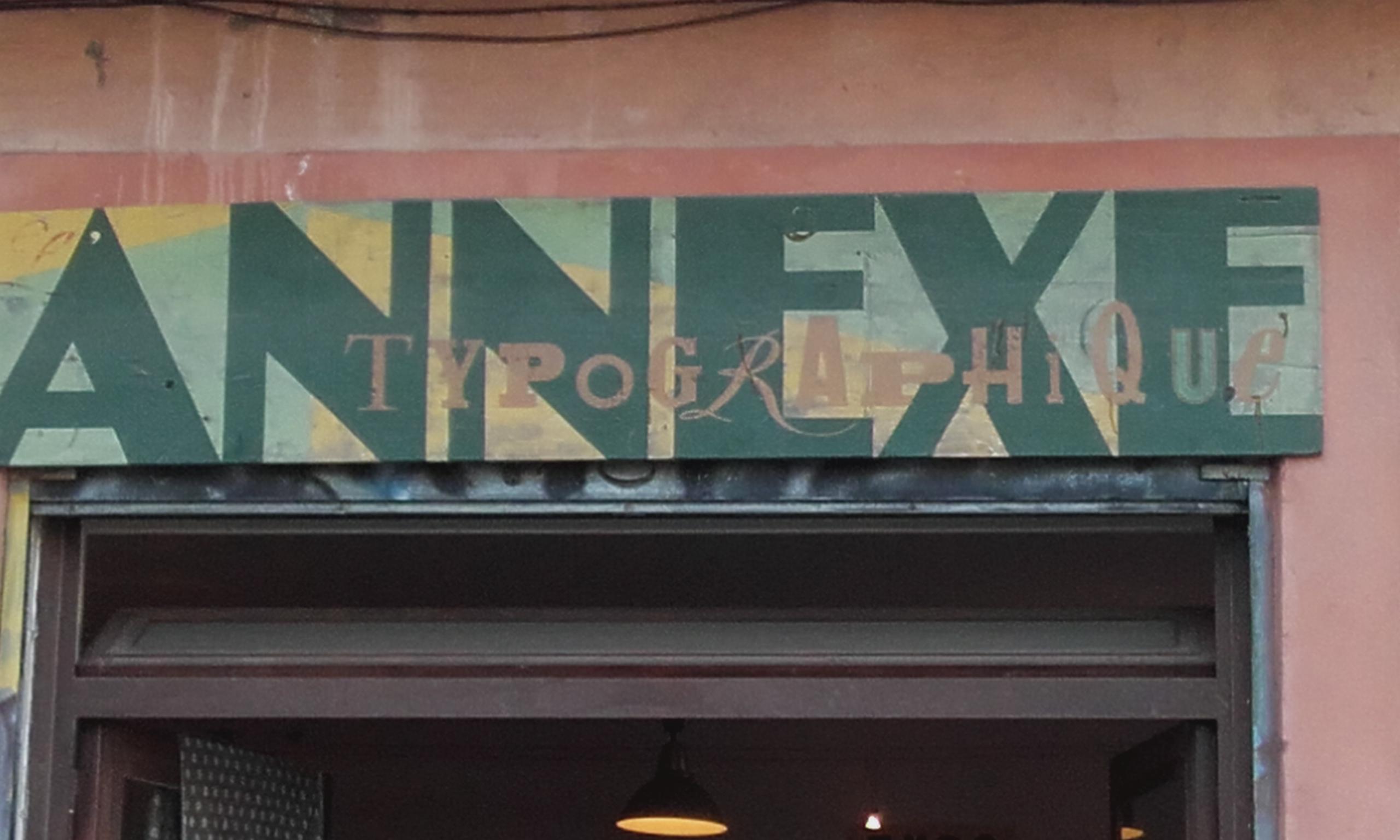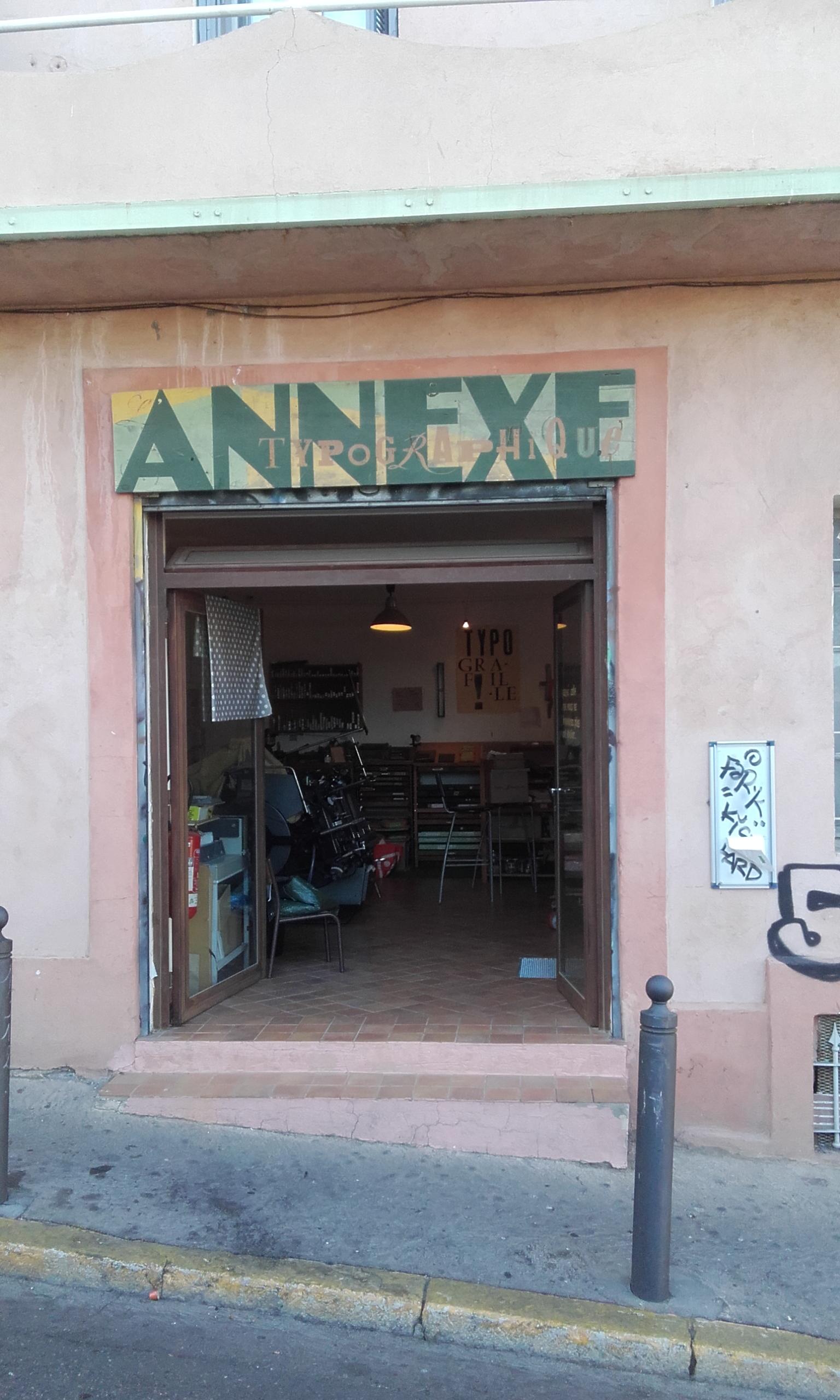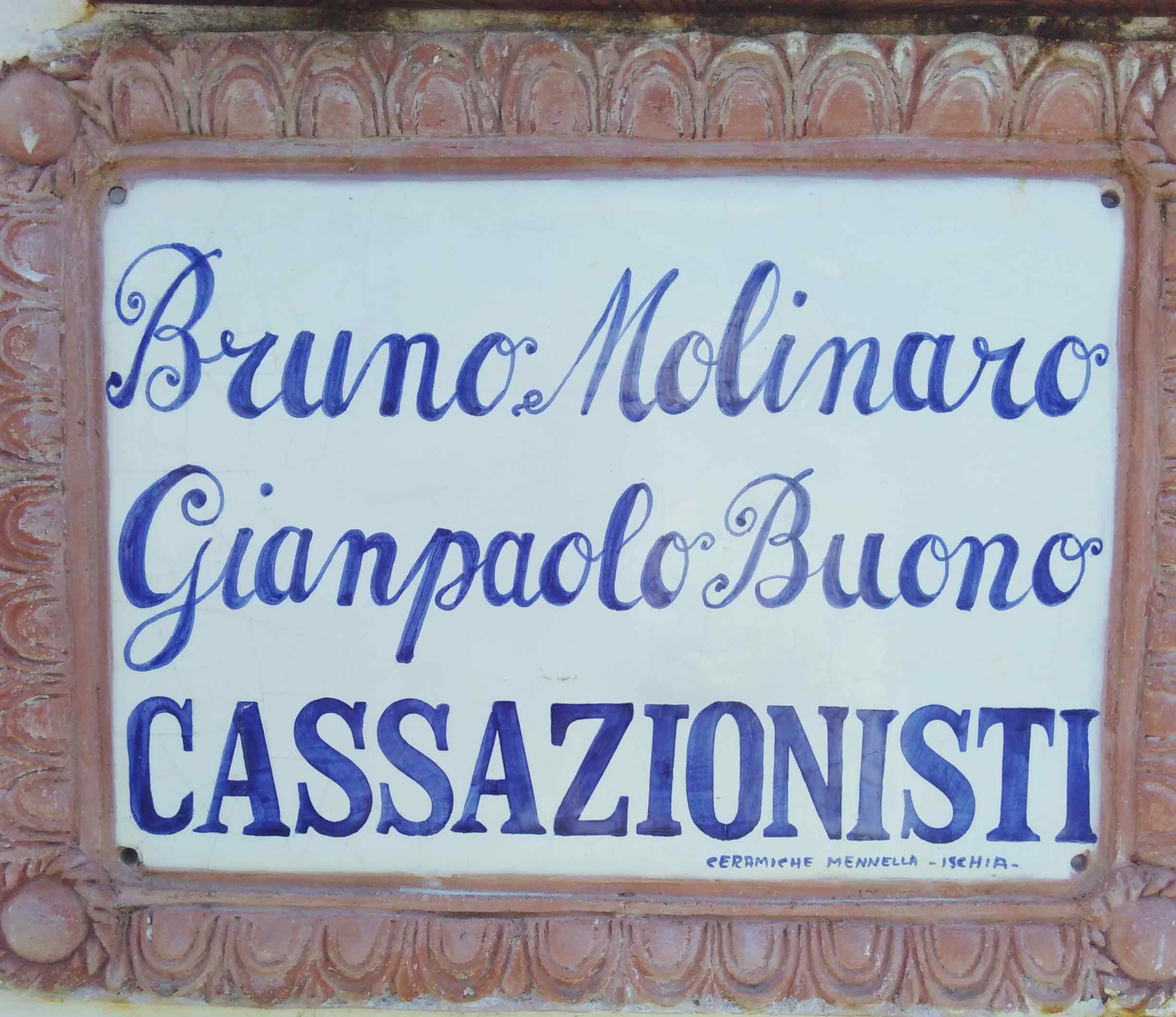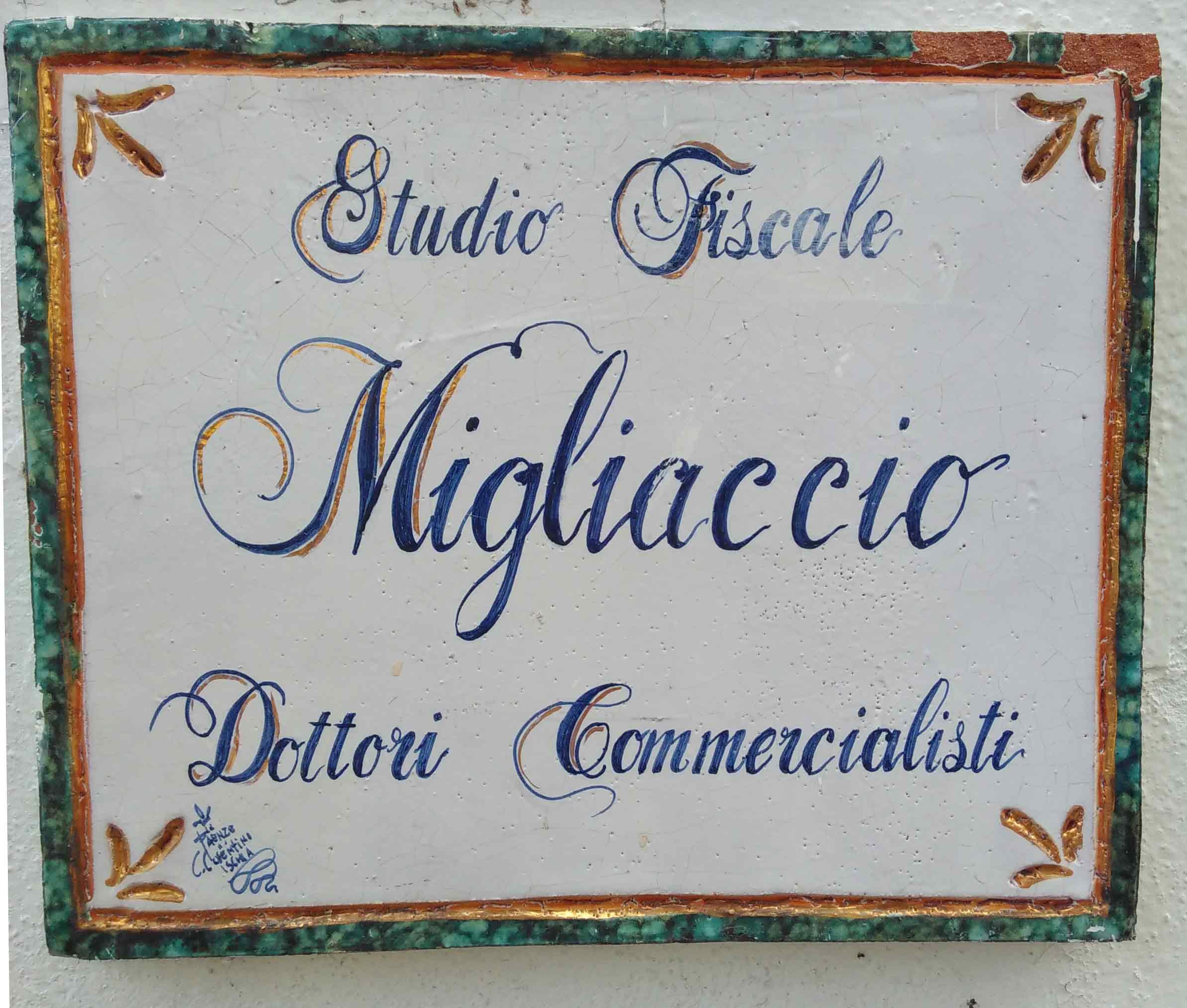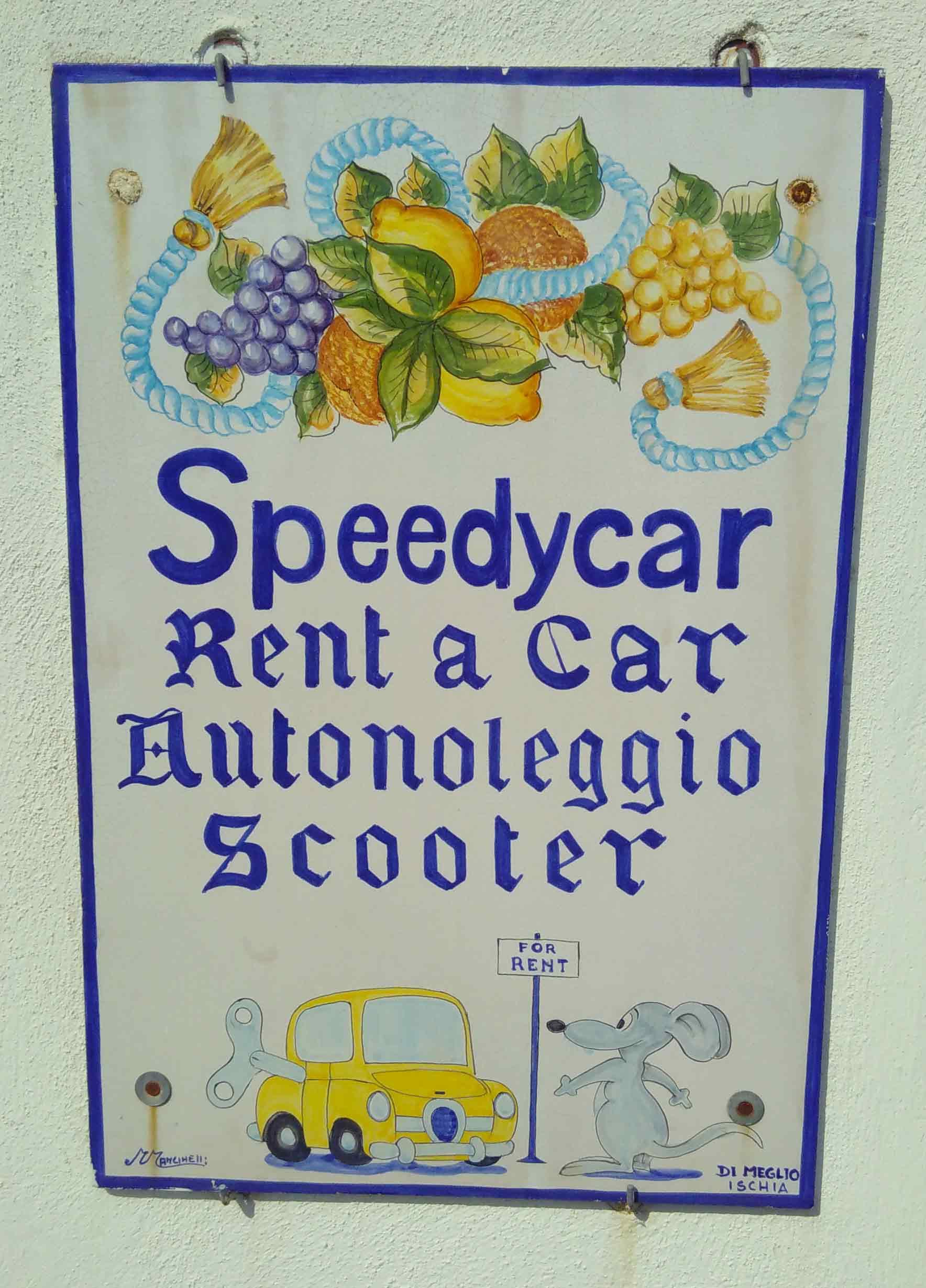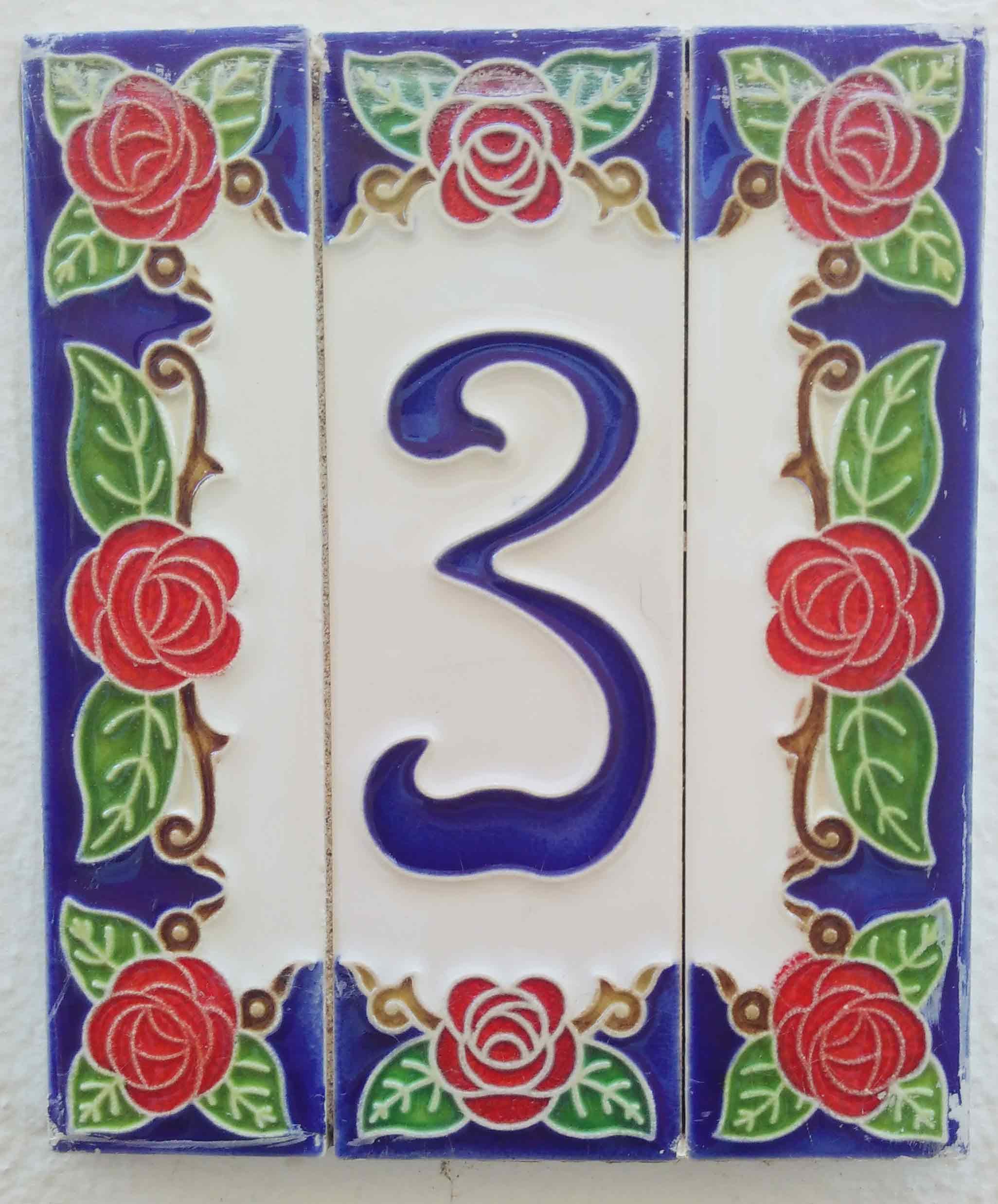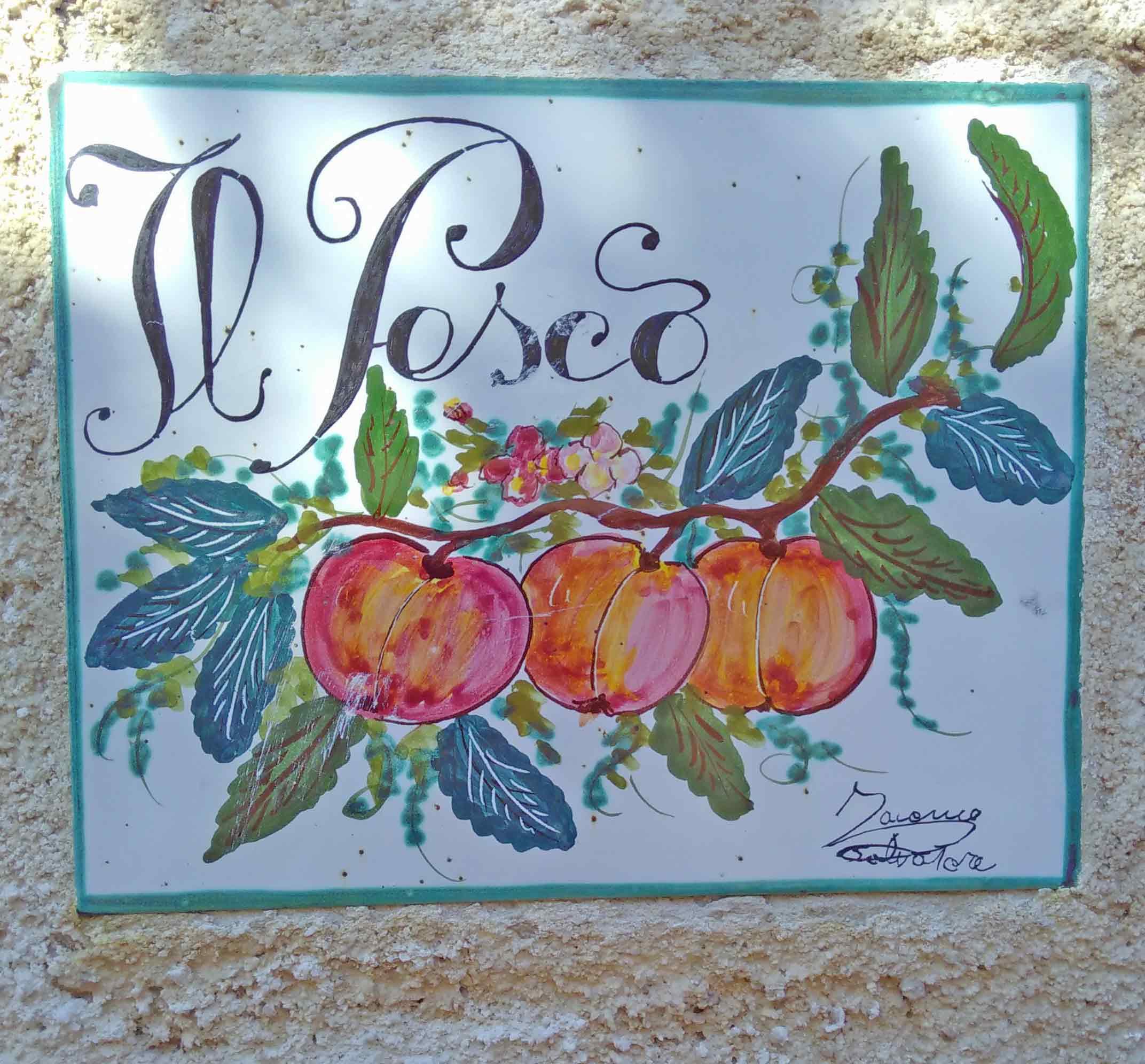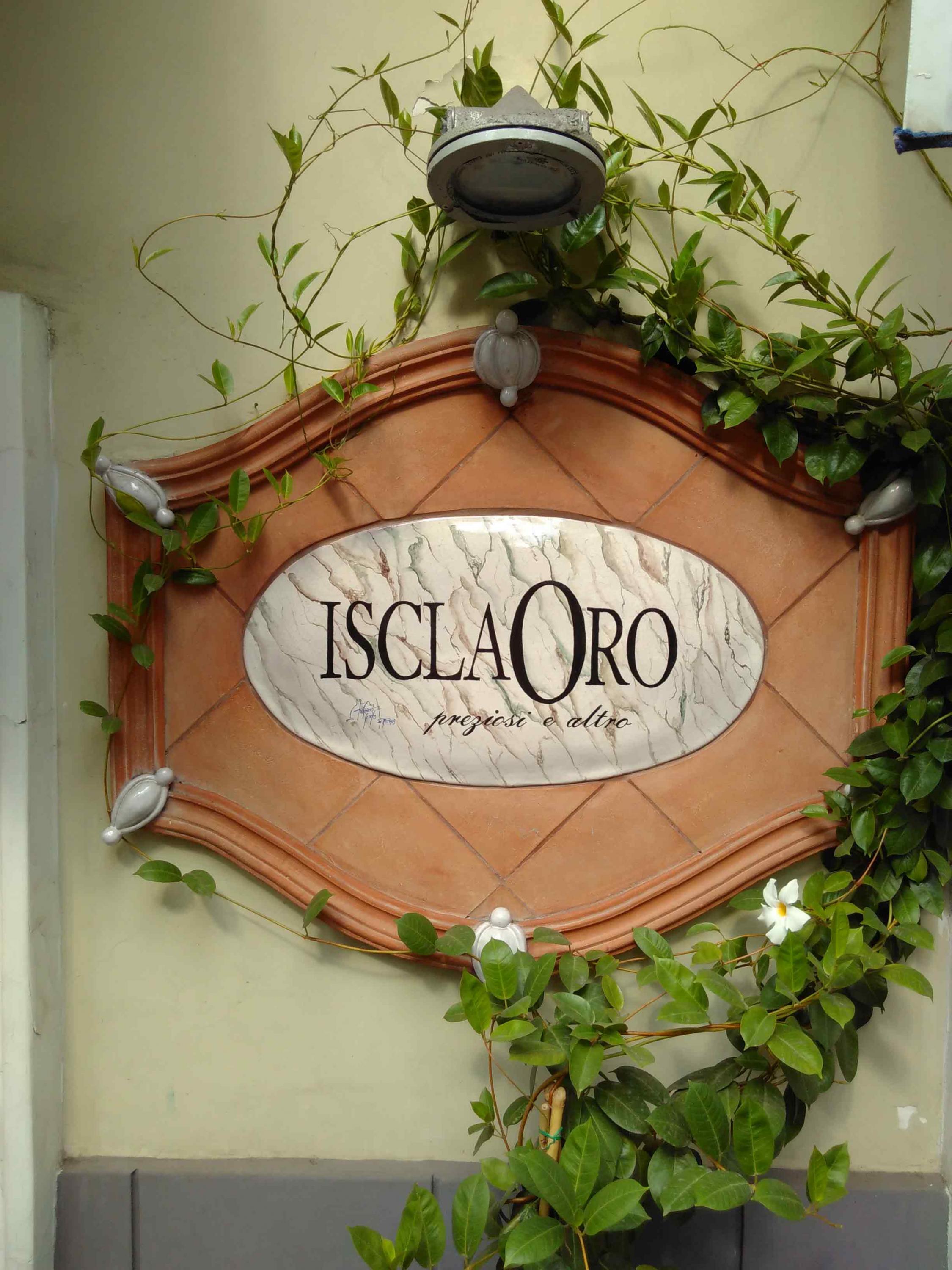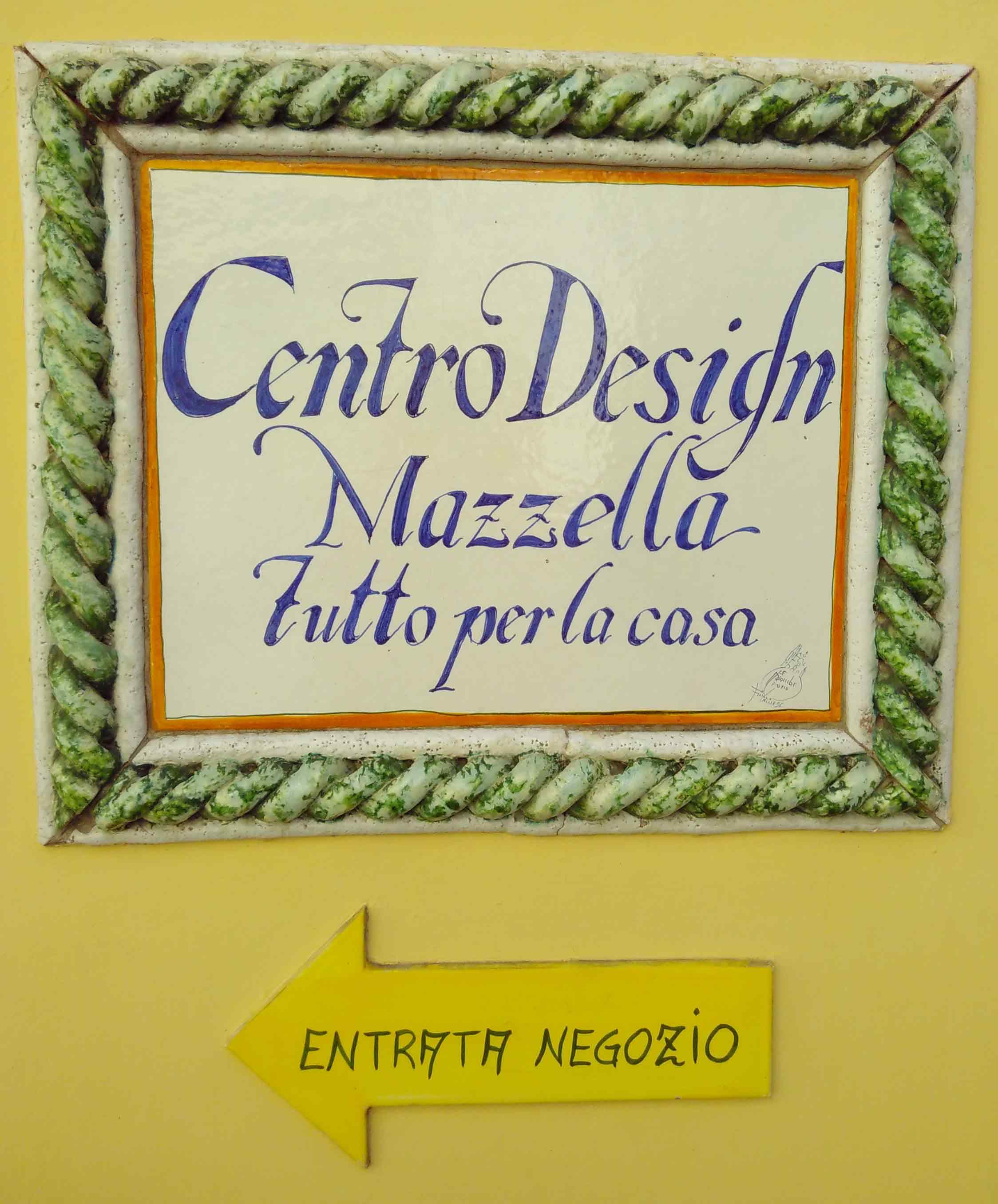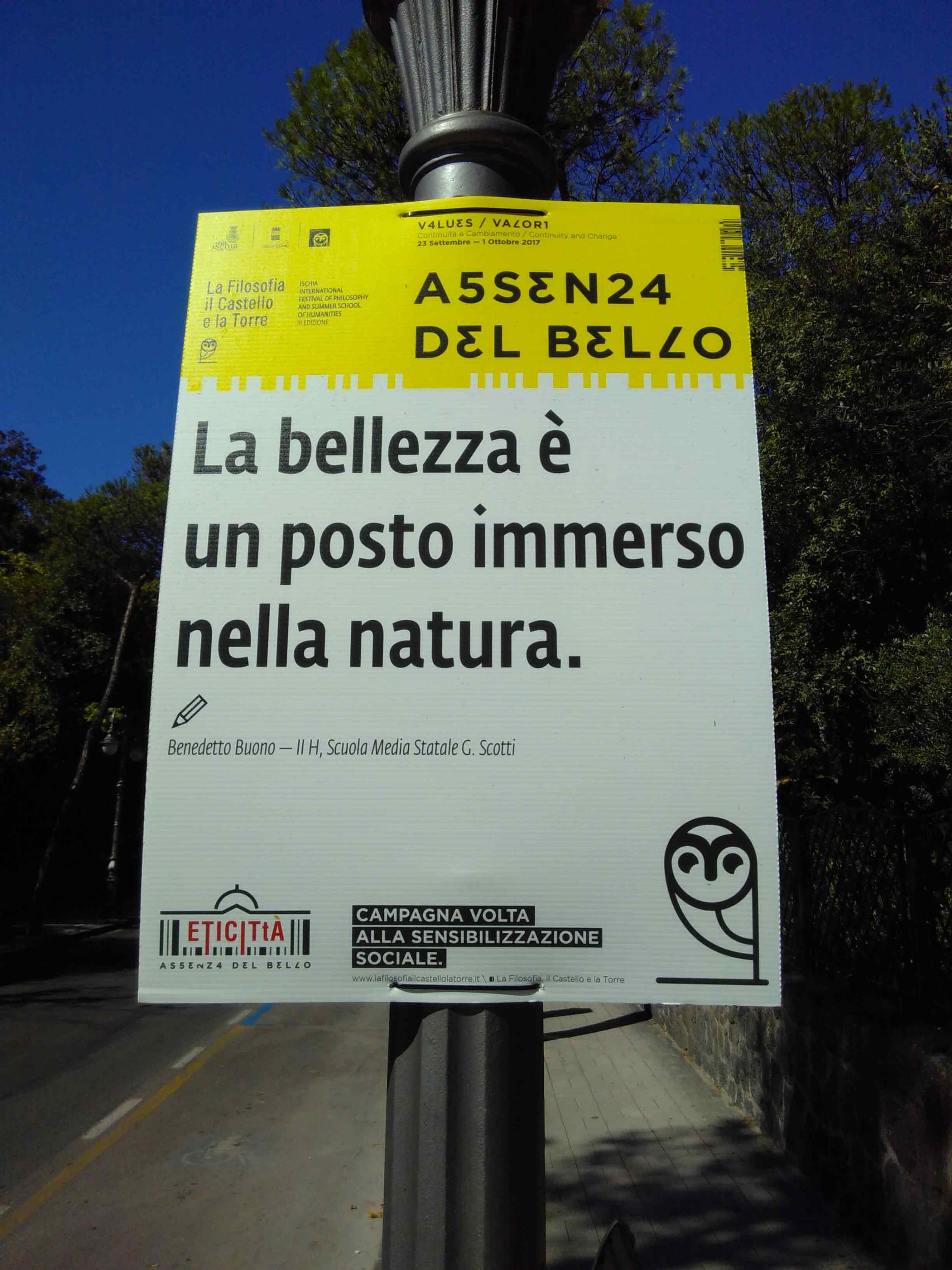
Wie Du sicherlich auch sehen kannst, sind hier die jeweils gleichen Buchstaben alle einen Hauch anders.
Und dann sind die jeweils gleichen Buchsteben nicht irgendwie zufällig anders, sonder anders, weil ihnen derBuchstabe davon unterschiedlich Platz lässt - siehe A in Artikel, oder A in WESTFALEN. All dies lässt sich bis heute so in einem Font nicht nachbauen, daher ist dies ein nahezu untrügliches Zeichen, das dies hier alles von Hand geschrieben wurde. Kalligafie...
Hatten wir das schon?
Ist doch offensichtlich. Alle verfügbaren Fs wurden für die nächste Zeile benötigt (die wegen des dramatischen Effekts erst auf der nächsten Slide zu sehen ist):
Heute ist mir die Broschüre »Das Berger-Zenz-Lied aus Reith bei Unken und die Hintergründe seines Entstehens« (Nr. 27 der Kniepaß-Schriften) in die Finger geraten. Darin ist die Sterbeparte von Vinzenz Wörgötter abgebildet. Ich kann mich nicht entsinnen, schon mal ein solches »W« gesehen zu haben:
Oh danke. Natürlich hat jeder die Cloister schon mal irgendwo gesehen. Aber das große »W«, das aussieht als ob es aus zwei Buchstaben zusammengesetzt wäre, habe ich heute erstmals bewusst wahrgenommen.
Gefunden auf Ischia.
Hammer.
›Die Wahrheit‹ in der taz von heute:
Jetzt wurde schon extra auf den Deppenzeilenumbruch verzichtet und es ist schon wieder nicht richtig...